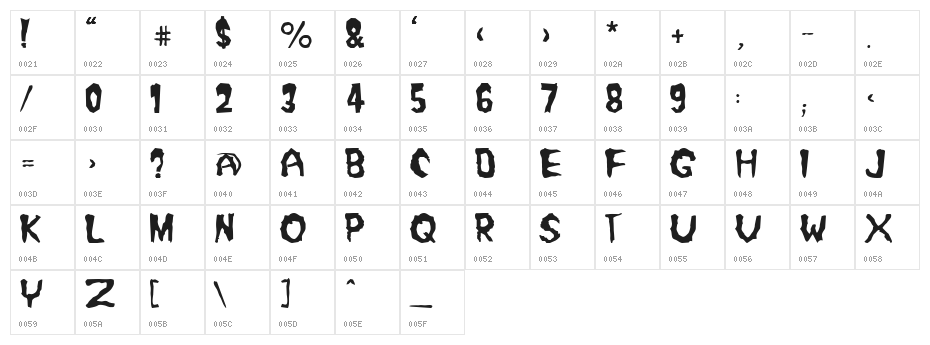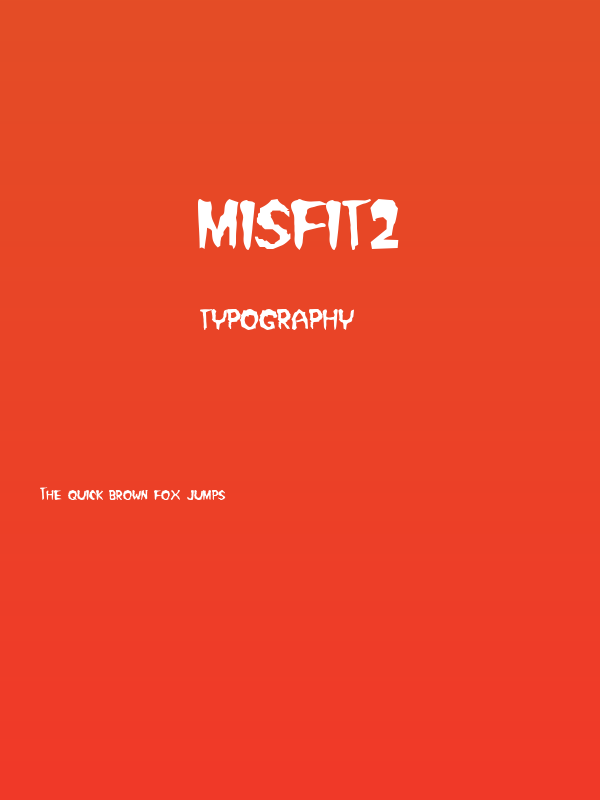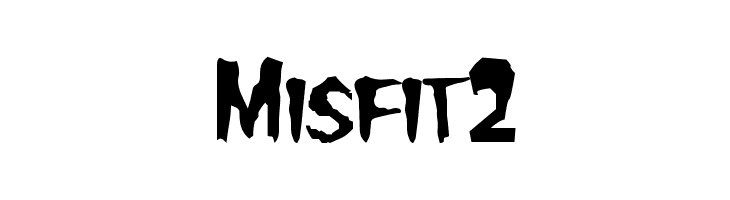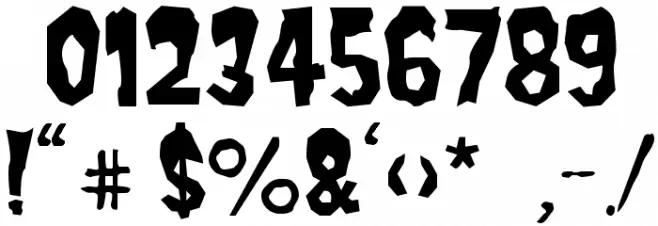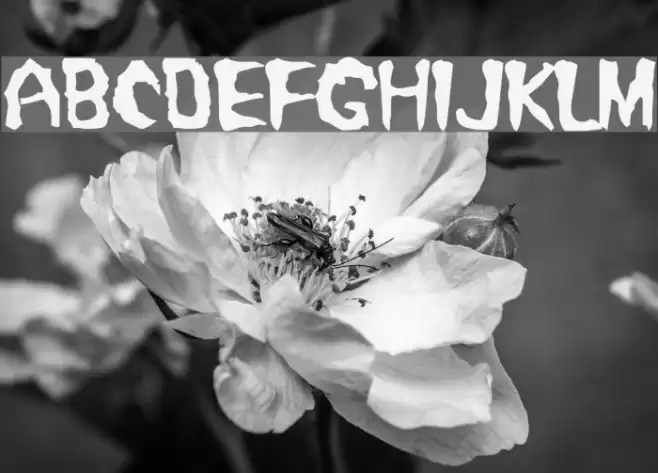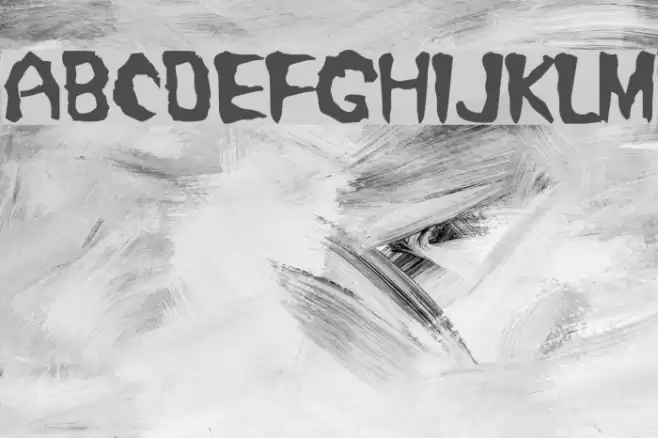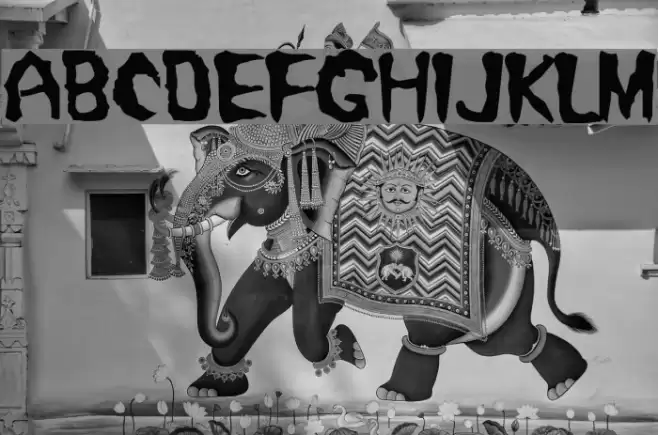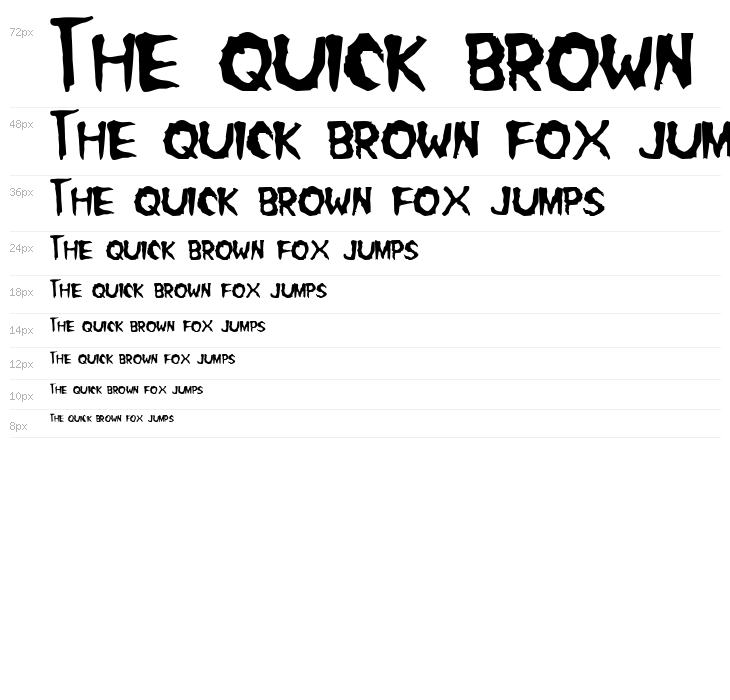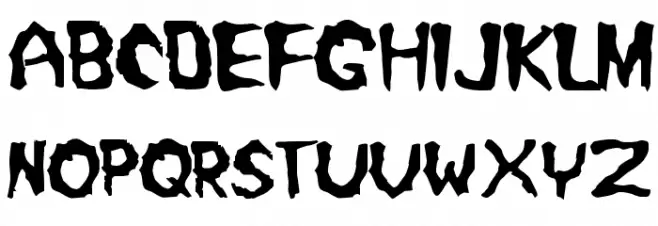
Misfit2 Font
| समग्र शैली | Edgy, Rebellious, Raw |
| उपयोग का मामला | Headlines, Logos, Posters |
| सुझाए गए प्रोजेक्ट | Ideal for music album covers, posters, branding for edgy products, and any design needing a rebellious touch. |